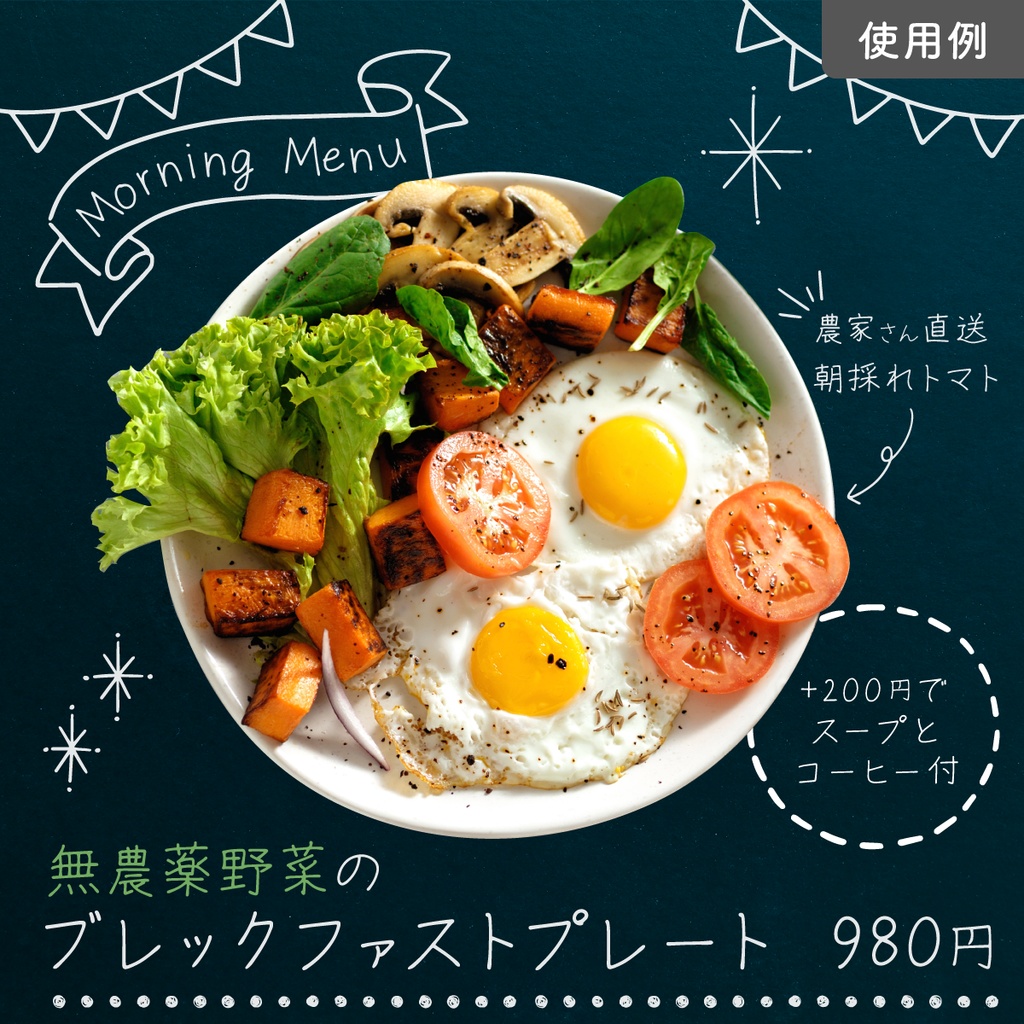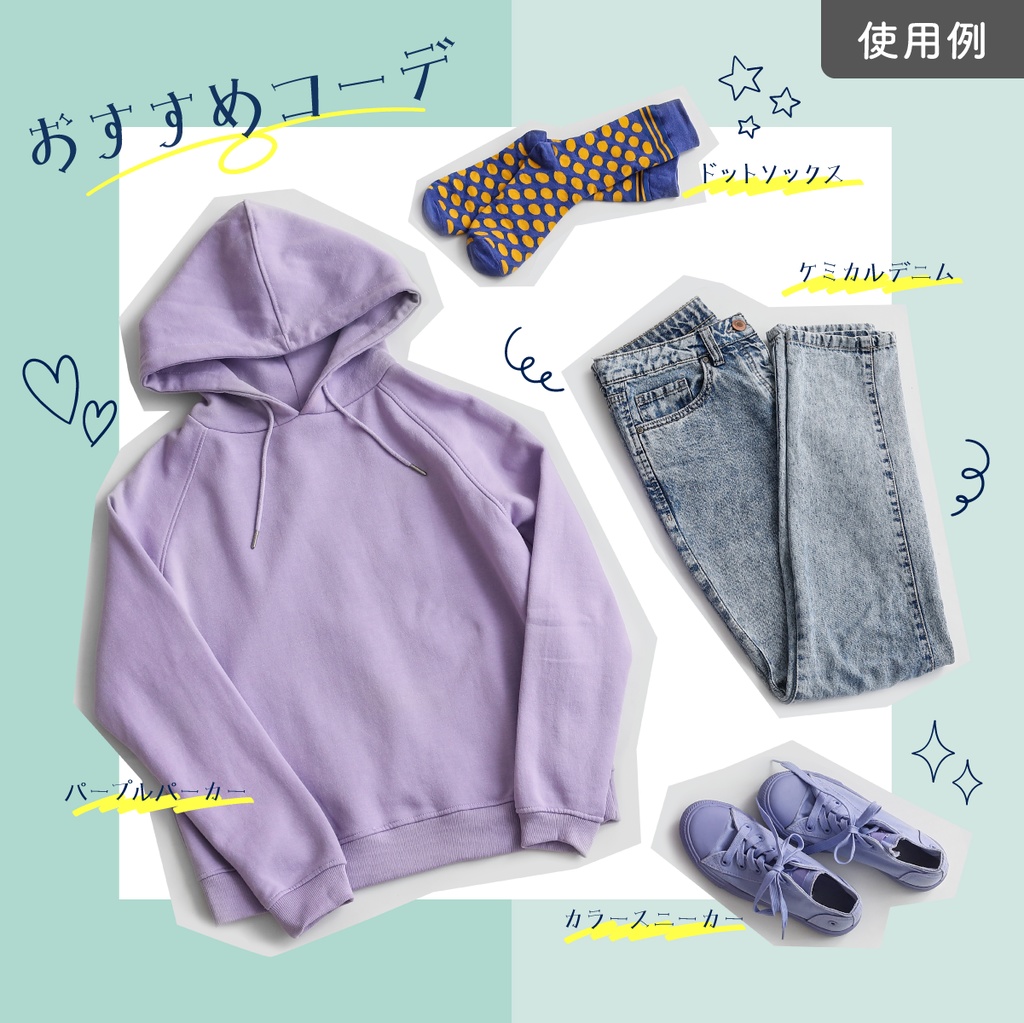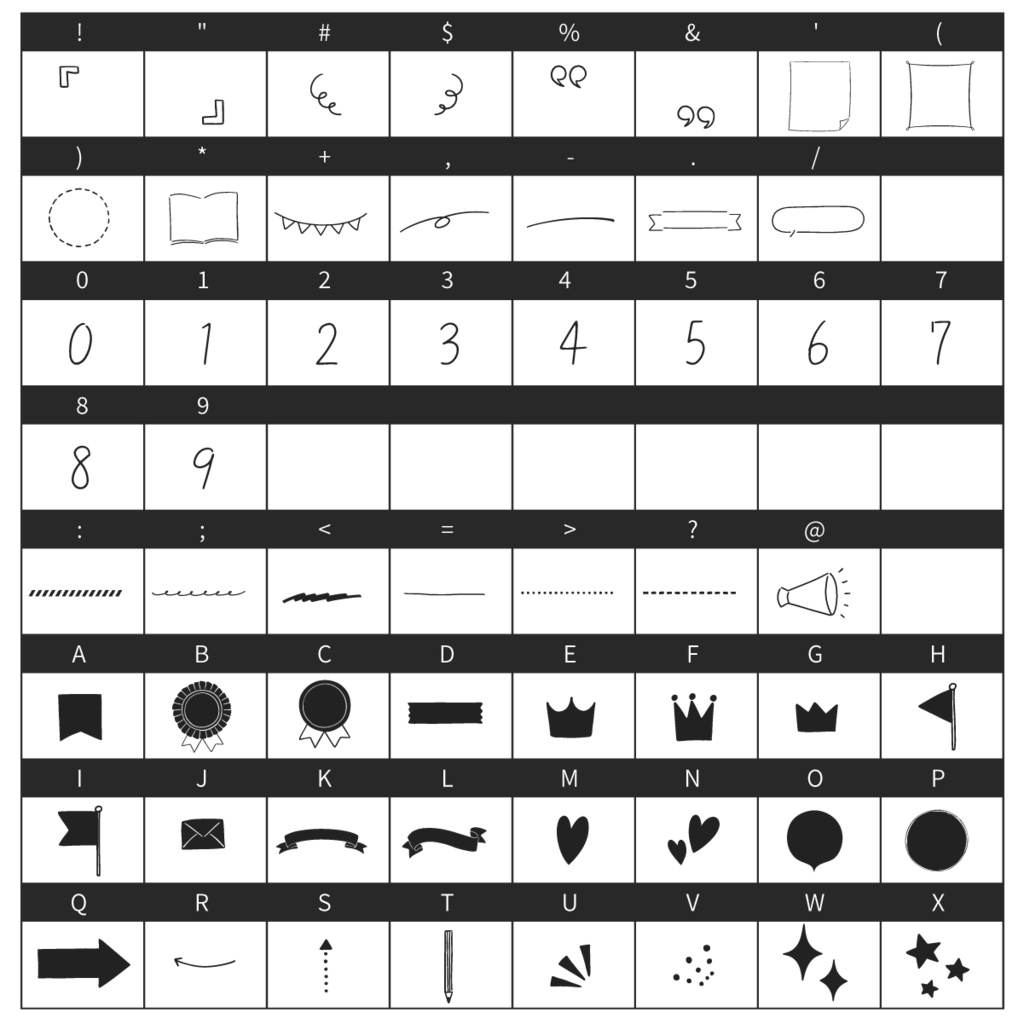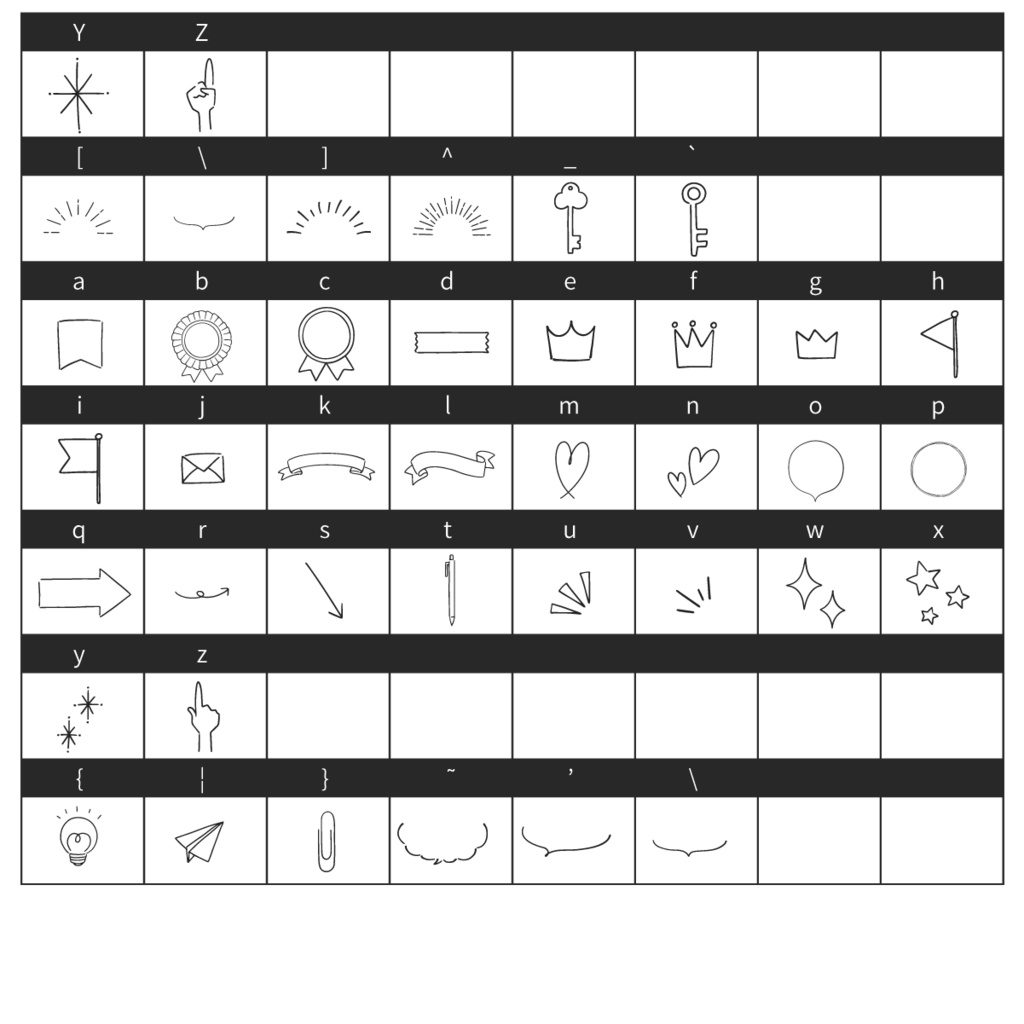
あしらいフォント「FURIKAKE! Hand drawing」
どんなフォント?
バナーやウェブデザイン、グラフィックなど、あしらいに使える飾りを欧文フォント化しました。 出てくるかざりは手描きで描いたものを取り込みました。 可愛くなりすぎないようシンプルで使い勝手が良いものを集めています。 なんとなく物足りないデザインにふりかけるように使っていただけたらなと思います。 アルファベット1文字につき1つの飾りが打て、98個の文字と飾りが収録されています。 飾りだけでなく数字と一部の文字も収録しているのでセール用バナーなどはこのフォントだけで作ることも可能です。 また商用にもお使いいただけます。 ベクターフォントなので画像化しない限りどこまで大きくしても画質が荒れません。